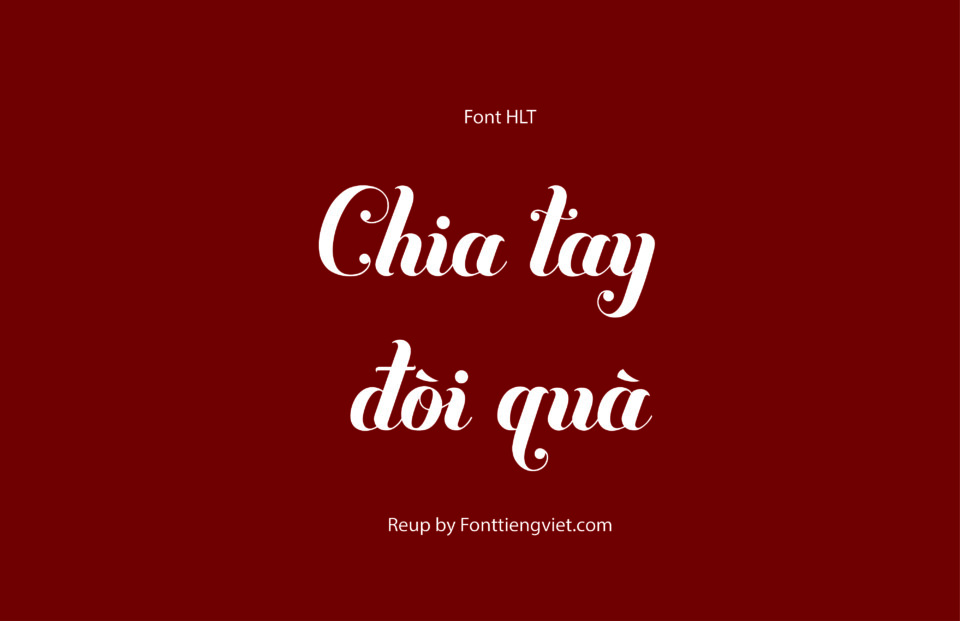
Font Việt hóa HLT Buttermilk
Giới thiệu về Font Việt hóa HLT Buttermilk
Trong thế giới đồ họa hiện đại, việc lựa chọn Font Miễn Phí phù hợp đóng vai trò quyết định đến sự thành công của một tác phẩm. Font Việt hóa HLT Buttermilk là một trong những bộ phông chữ viết tay mang phong cách thư pháp nghệ thuật vô cùng độc đáo. Với những đường nét mềm mại, uyển chuyển và đầy tinh tế, bộ font này giúp các bạn học sinh và giáo viên dễ dàng tạo ra những slide bài giảng sinh động hay những tấm thiệp chúc mừng ý nghĩa. Đặc biệt, phiên bản này đã được tối ưu hóa tiếng Việt hoàn chỉnh, giúp người dùng không còn lo lắng về lỗi hiển thị dấu câu khi soạn thảo văn bản trên các phần mềm thiết kế chuyên nghiệp.
Đặc điểm nổi bật của phông chữ
Font Việt hóa HLT Buttermilk sở hữu cấu trúc các ký tự bay bổng nhưng vẫn giữ được độ rõ nét cần thiết. Đây là lựa chọn lý tưởng cho các dự án yêu cầu sự nữ tính, nhẹ nhàng như thiết kế logo, bìa sách, hoặc trang trí ảnh kỷ yếu trường lớp. Khả năng kết hợp linh hoạt của nó với các font chữ không chân khác sẽ tạo nên sự tương phản thú vị, giúp nội dung truyền tải trở nên thu hút và chuyên nghiệp hơn bao giờ hết trong mắt người xem.
Cách sử dụng Font Việt hóa HLT Buttermilk hiệu quả
Để phát huy tối đa vẻ đẹp của bộ font này, bạn nên sử dụng nó cho các tiêu đề lớn hoặc những câu trích dẫn ngắn gọn. Việc lạm dụng phông chữ viết tay cho các đoạn văn bản dài có thể gây mỏi mắt, vì vậy hãy khéo léo lồng ghép để tạo điểm nhấn thị giác. Ngoài ra, hãy thử thay đổi màu sắc và thêm các hiệu ứng đổ bóng nhẹ để làm nổi bật những đường cong đặc trưng của chữ.